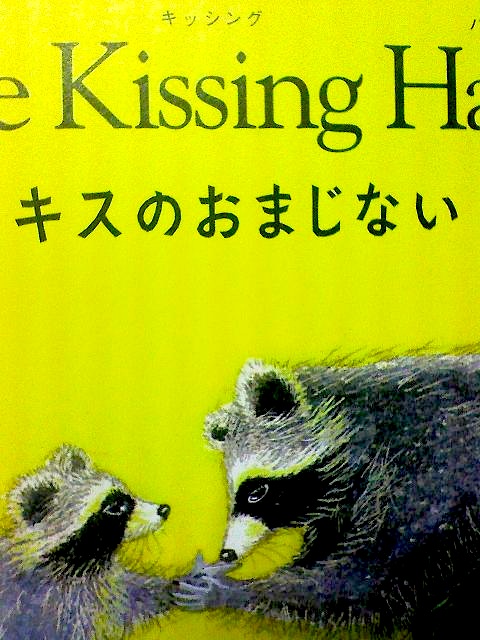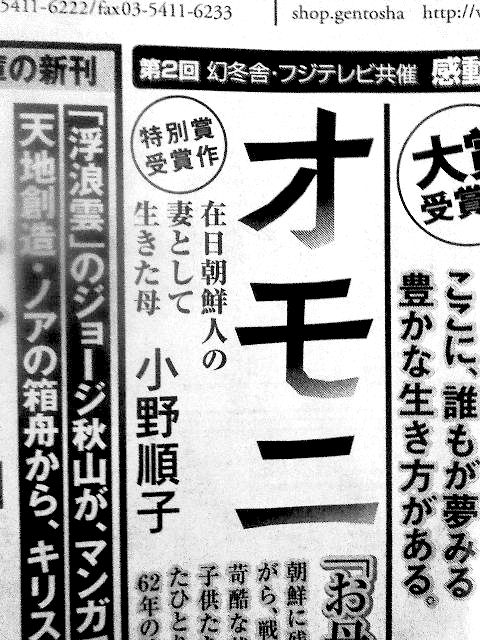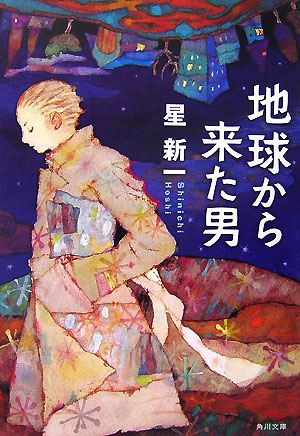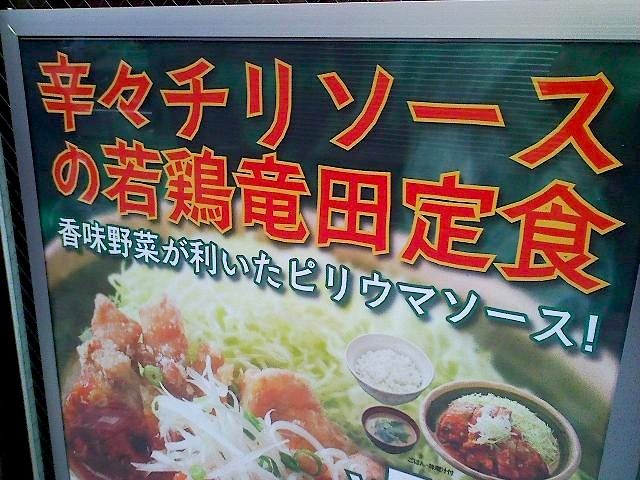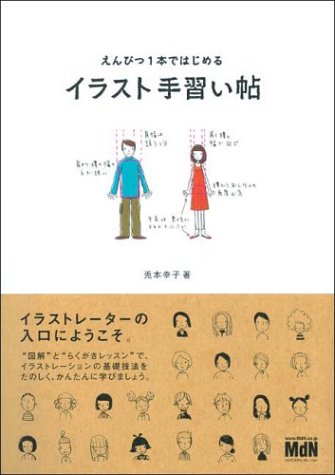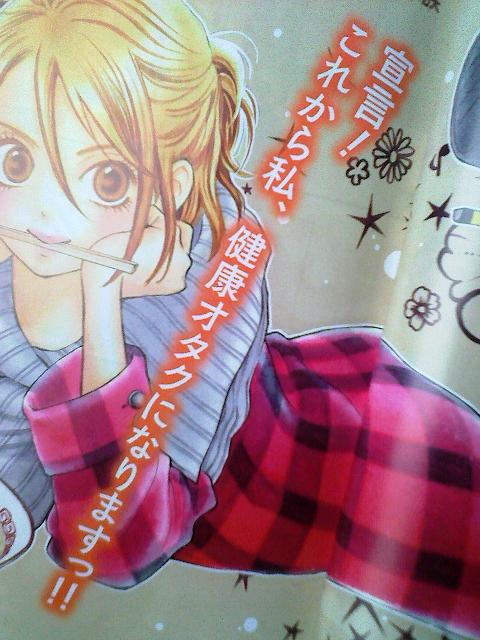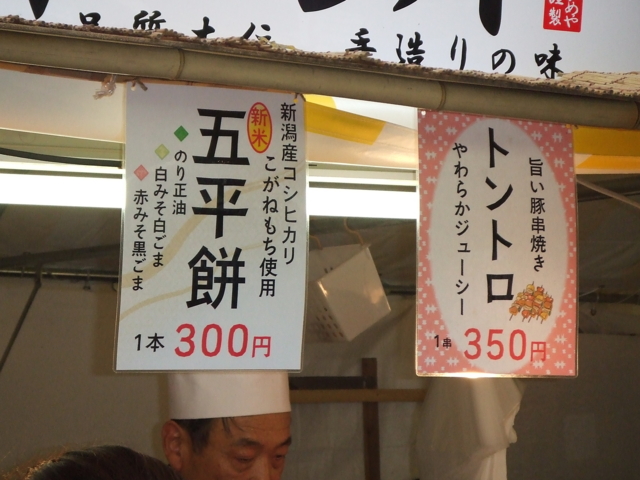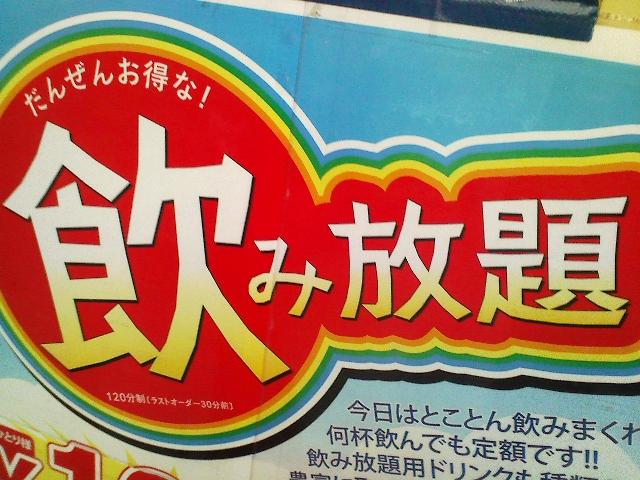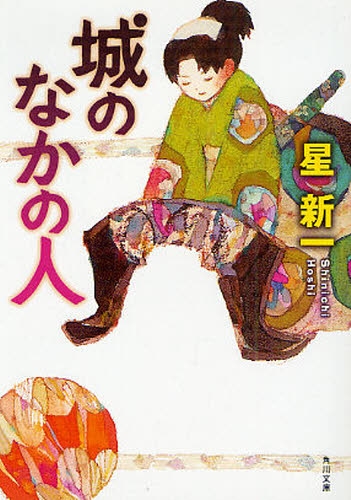
第57回江戸川乱歩賞受賞作  さとうゆたか  2011年8月12日(金) 8:18
本の表紙。書名と著者名に使われています。
書名:完盗オンサイト
著者:玖村まゆみ
発行:講談社
名古屋鉄道の定期マガジン  名無し  2011年7月26日(火) 23:04
の16、17ページであられが使われてました。
さとうゆたか  2011年7月27日(水) 8:11 [修正]
これですね。
てなしも  2011年5月7日(土) 20:26
ディズニーものなので画像の掲載は難しいかもしれませんが…
書籍のタイトルにあられがかなり大きいサイズで使われていました。
さとうゆたか  2011年5月7日(土) 20:58 [修正]
この書籍ですね↓
書名:ディズニーの素敵な切り絵
著者:桜まあち
発行:ブティック社
本の表紙  さとうゆたか  2011年5月2日(月) 16:18
書名:よくわかる中国語文法
著者:丸尾 誠
発行:アスク
よくわかる!シリーズ  さとうゆたか  2011年1月28日(金) 9:46
販売時に巻かれている帯にも使われています。
書名:面白くてよくわかる!日本史
監修:加来 耕三
発行:アスペクト
さとうゆたか  2011年1月28日(金) 22:08 [修正]
これも同じシリーズですね。
おらほの屋のWebサイト  さとうゆたか  2010年12月31日(金) 16:01
カラメルショップ大賞2010で、ショップデザイン賞グランプリを獲得したサイトのトップ画像。
おらほの屋
「カラメル」は、出店数16000以上のショッピングモールです。
さとうゆたか  2010年12月31日(金) 16:06 [修正]
この他にも、サイト内のあちこちに「あられフォント」が効果的に使われています。
おらほの屋
さとうゆたか  2010年12月31日(金) 16:41 [修正]
もうひとつ。
使用されている場所は、もっとありますけど、あとは「おらほの屋」のサイトを御覧ください。
お茶漬けのTVCM  さとうゆたか  2010年12月15日(水) 17:27
丸美屋の製品CMです。
さとうゆたか  2010年12月15日(水) 17:28 [修正]
こちらも。
漫画のタイトル  さとうゆたか  2010年9月28日(火) 8:55
女性向け漫画雑誌で。
作者は「もんでんあきこ」
橋本大二郎氏のブログに  谷岡  2010年8月20日(金) 1:44  HP
橋本大二郎前高知県知事のブログタイトル題字に、
あられが使われているようです。
さとうゆたか  2010年8月20日(金) 8:27 [修正]
これですね。
漫画の扉ページ  さとうゆたか  2010年2月28日(日) 10:04
スペリオールに連載中の「はんなり」という柴門ふみの漫画。